Bạn là designer, marketer hay fan của văn hóa Nhật Bản? Việc sử dụng font chữ Nhật phù hợp sẽ giúp thiết kế của bạn nổi bật và mang đậm dấu ấn xứ sở hoa anh đào. Danh sách +77 font chữ Nhật Bản “chuẩn xịn” dưới đây sẽ giúp bạn thoải mái sáng tạo mà không lo lỗi font.
Vì sao font chữ tiếng Nhật Bản được ưa chuộng?
Sau khi hiểu lý do vì sao font tiếng Nhật Bản được ưa chuộng, hãy cùng khám phá chi tiết từng yếu tố nổi bật giúp chúng trở thành lựa chọn hàng đầu trong thiết kế:
Mang đậm dấu ấn văn hóa Nhật
Font chữ Nhật Bản không chỉ đơn thuần là kí tự mà còn phản ánh tinh hoa văn hóa lâu đời của xứ sở hoa anh đào. Các đường nét gợi nhắc đến nghệ thuật thư pháp Shodō, sự tinh tế trong cách người Nhật trân trọng từng chi tiết.
Chính vì vậy, khi sử dụng font Nhật, thiết kế dễ dàng gợi liên tưởng đến anime, manga, sushi, trà đạo hay tinh thần “wabi-sabi” – vẻ đẹp của sự giản dị và không hoàn hảo. Điều này giúp người xem ngay lập tức kết nối với một không gian mang bản sắc Nhật Bản.
Dễ tạo điểm nhấn trong thiết kế
Trong bối cảnh hàng ngàn mẫu thiết kế xuất hiện mỗi ngày, font tiếng Nhật Bản mang lại sự khác biệt rõ rệt. Các đường nét vuông vức, mạnh mẽ nhưng vẫn uyển chuyển giúp nội dung trở nên bắt mắt, dễ ghi nhớ. Ngoài ra, các font chữ Nhật cũng có thể Việt Hoá lên để tạo font chữ đẹp khi làm các sự kiện, thiết kế liên quan đến văn hoá Nhật.
Dù chỉ dùng cho tiêu đề poster, logo, hay vài dòng nhấn nhá trên banner, font Nhật vẫn có thể “giữ spotlight”. Đây cũng là lý do nhiều nhà hàng, thương hiệu thời trang, hay studio thiết kế lựa chọn font Nhật để khẳng định phong cách riêng.
Hợp xu hướng thiết kế tối giản, tinh tế
Triết lý Minimalism (tối giản) đang trở thành xu hướng toàn cầu, từ kiến trúc, nội thất cho đến thiết kế đồ họa. Font chữ Nhật Bản vốn mang cấu trúc gọn gàng, rõ ràng, ít chi tiết rườm rà, vì vậy cực kỳ phù hợp với phong cách này.
Chúng không chỉ giúp người đọc dễ tiếp nhận thông tin mà còn thể hiện gu thẩm mỹ tinh tế. Đặc biệt, khi kết hợp font Nhật với các bảng màu trung tính (đen, trắng, be) hoặc layout thoáng đãng, tổng thể thiết kế sẽ vừa hiện đại vừa sang trọng.
Tổng Hợp +77 Font Chữ Nhật Bản Hot Nhất
Những nhóm font tiếng Nhật Bản không chỉ đa dạng về hình thức mà còn phù hợp với nhiều phong cách thiết kế khác nhau. Tiếp theo, chúng ta sẽ tìm hiểu chi tiết từng nhóm font, từ thư pháp truyền thống đến phong cách hiện đại và Anime/Manga.
Font thư pháp Nhật (Brush/Calligraphy)
Đây là nhóm font mô phỏng nét bút lông truyền thống, mang hơi thở của nghệ thuật thư pháp Nhật. Các nét chữ mềm mại nhưng mạnh mẽ, thể hiện sự uyển chuyển và tinh thần Zen. Font thư pháp thường dùng trong thiết kế mang đậm tính văn hóa như poster sự kiện, quán ăn Nhật, trà đạo hoặc bìa sách nghệ thuật.
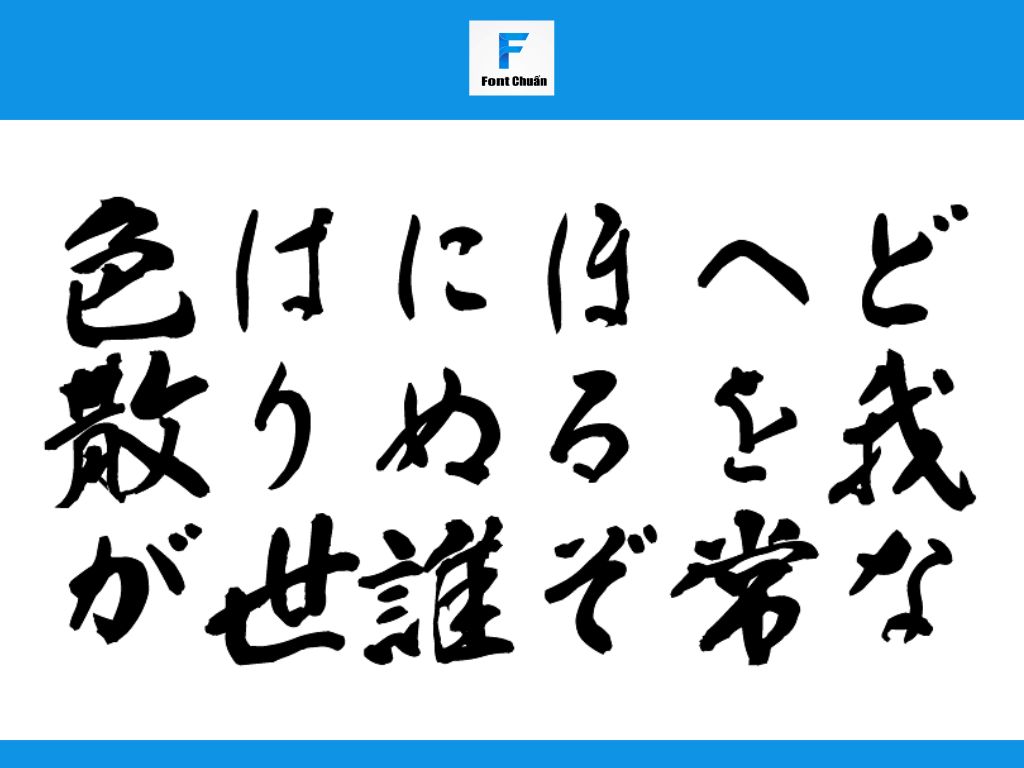
Font Nhật hiện đại (Gothic, Sans Serif)
Nhóm font này có đặc trưng gọn gàng, tối giản, dễ đọc, phù hợp với xu hướng thiết kế hiện đại. Bạn sẽ thường thấy chúng xuất hiện trong logo thương hiệu, website, banner quảng cáo hay brochure. Gothic và Sans Serif Nhật không chỉ mang tính thẩm mỹ mà còn đảm bảo sự chuyên nghiệp trong truyền tải thông tin.
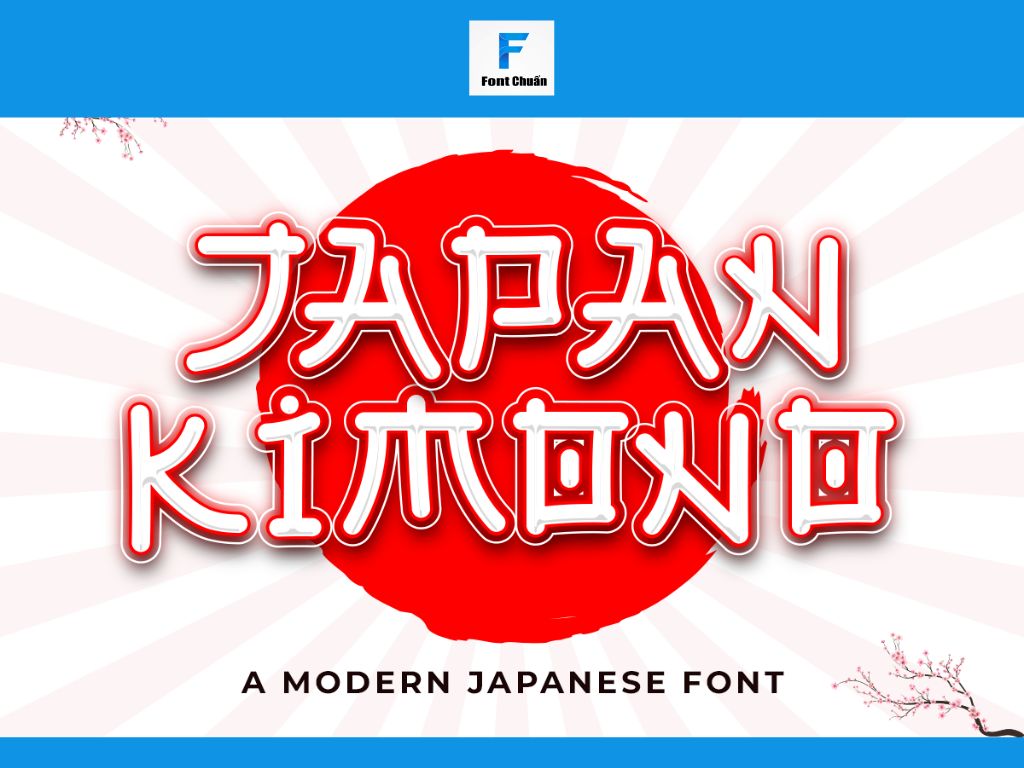
Font chữ Nhật phong cách Anime/Manga
Được lấy cảm hứng từ truyện tranh và phim hoạt hình Nhật Bản, nhóm font này mang nét cá tính, sinh động, gần gũi với giới trẻ. Font Anime/Manga thường dùng trong poster phim, tiêu đề truyện tranh, game hoặc các sản phẩm giải trí, giúp tăng sức hút và tạo cảm giác vui tươi.
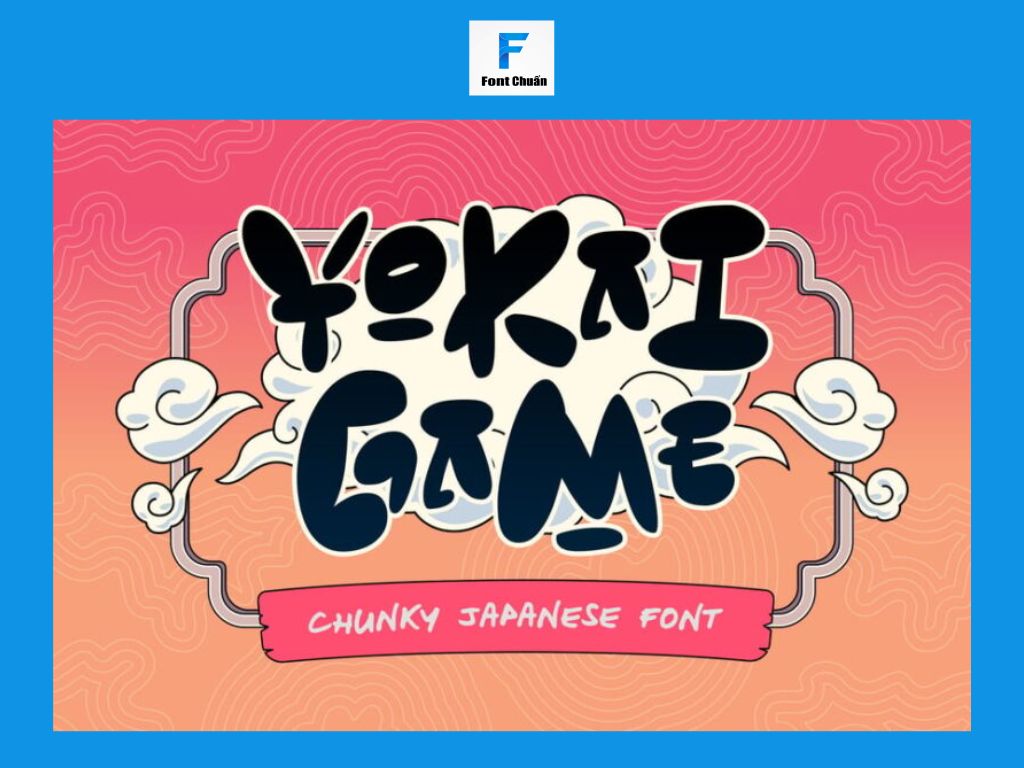
Font chữ Nhật Bản đẹp nên thử
Một vài font đẹp, được nhiều designer quốc tế ưa chuộng:
- Kozuka Gothic – hiện đại, dễ ứng dụng trong in ấn và web.
- Yu Mincho – thanh lịch, mang hơi thở truyền thống.
- Noto Sans JP – gọn gàng, chuẩn Unicode, tối ưu hiển thị trên mọi nền tảng.
- Tetsubin Gothic – mạnh mẽ, dễ kết hợp trong poster hoặc tiêu đề.
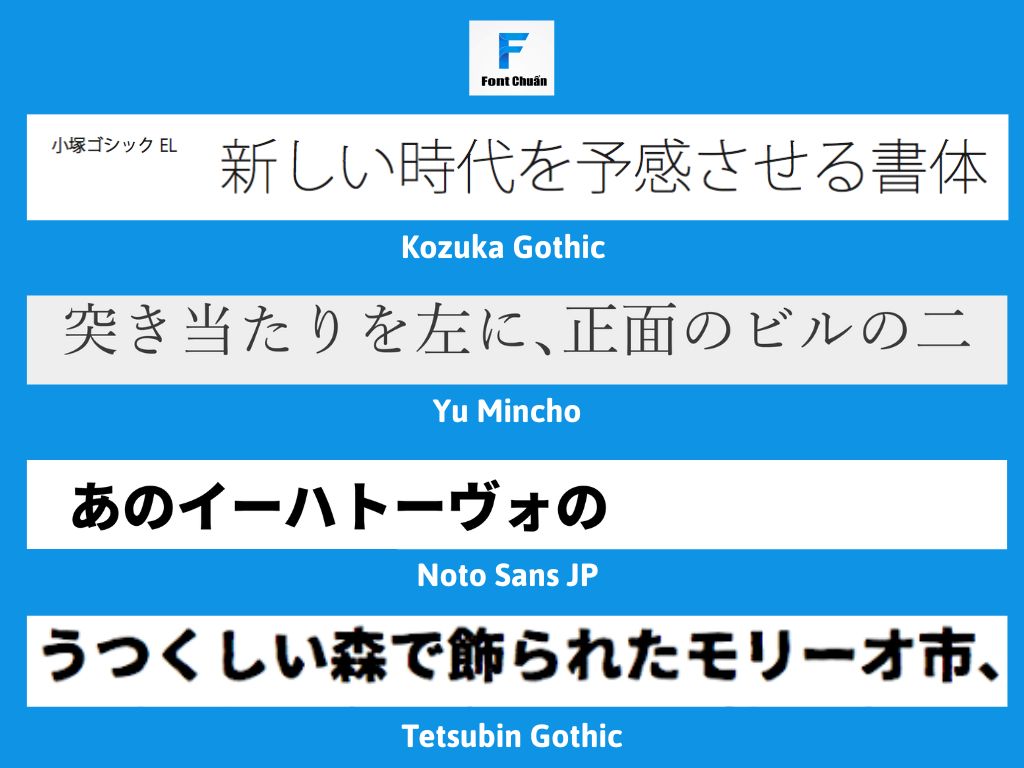
Mỗi font đều có ưu điểm riêng: từ sự mềm mại (Yu Mincho), tính phổ thông (Noto Sans JP) cho đến nét độc đáo cá tính (Anime Ace). Người thiết kế có thể tùy biến để phù hợp với dự án của mình.
Font chữ Nhật Việt hóa
Để dùng cho thiết kế tiếng Việt, bạn có thể tham khảo các bản font Việt hóa như:
- Kozuka Gothic Việt hóa
- Yu Gothic Việt hóa
- Noto Sans JP Việt hóa
Ưu điểm của font Việt hóa là hỗ trợ đầy đủ dấu tiếng Việt, tránh tình trạng lỗi hiển thị. Điều này giúp designer dễ dàng sáng tạo mà không cần chỉnh sửa thủ công.
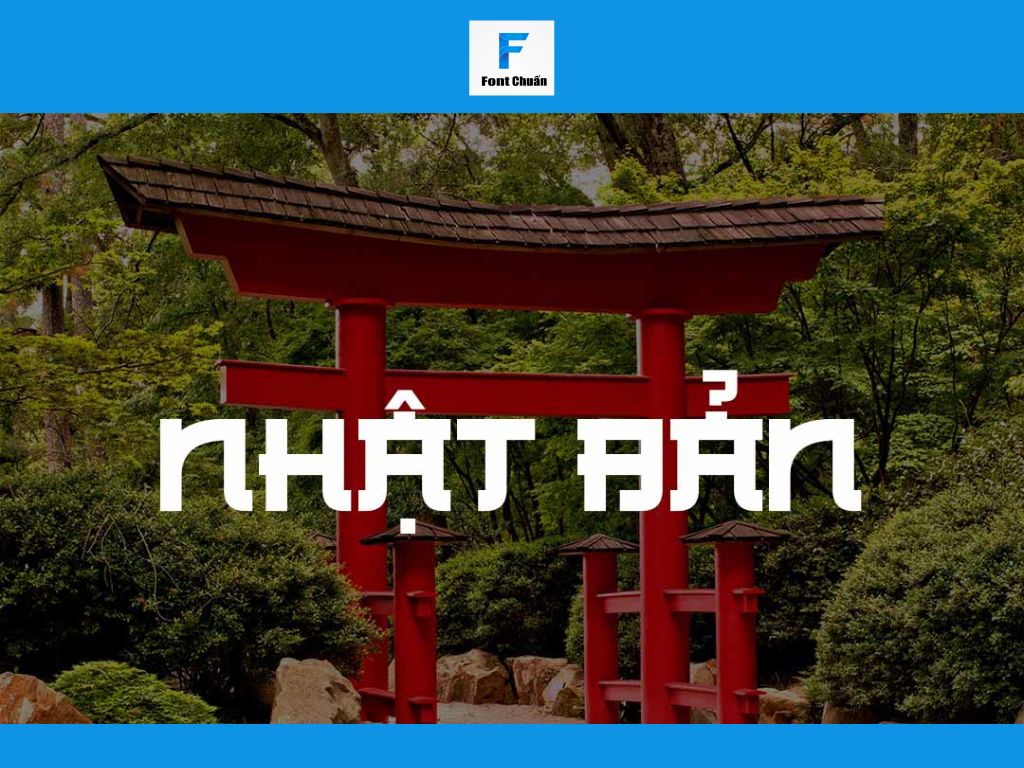
Font chữ Nhật Bản thường tạo cảm giác tinh tế và trầm lắng. Tuy nhiên, trong những thiết kế cần khai thác yếu tố rùng rợn hoặc căng thẳng, phông chữ kinh dị lại được sử dụng để đẩy mạnh cảm xúc thị giác.